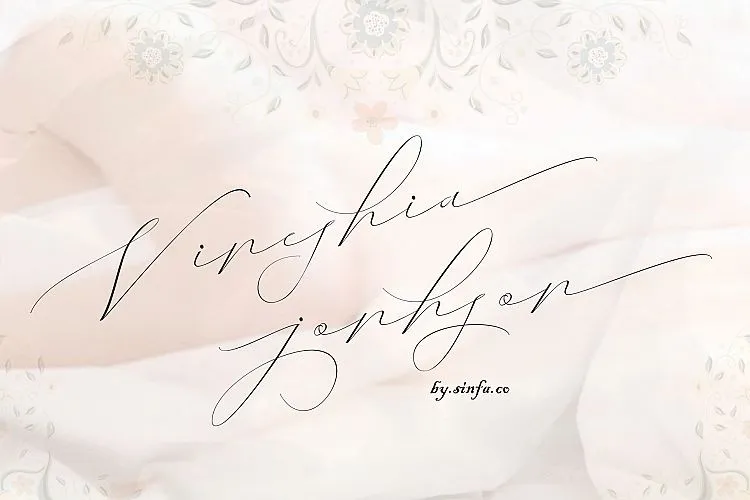
Vineshia Jonhson Handwritten Font – Fonte Grátis
Vineshia Jonhson Handwritten Font
Aqui está uma descrição em português para a página de download da fonte ‘Vineshia Jonhson Handwritten Font’, adaptada aos requisitos: Um novo conceito na categoria de fontes escrita à mão, essa moderna e feminina Vineshia Jonhson é perfeita para aqueles que desejam dar um toque único e criativo a seus projetos. Construída com uma estrutura elegante mas com traços casuais e bases variadas, permite criar um visual autêntico de escrita à mão. Esta fonte é ideal tanto para trabalhos manuais quanto para design tipográfico, permitindo que você realize diversas criações em poucas horas. Com seu desenho atrevido e sua personalidade única, a Vineshia Jonhson é uma excelente escolha para quem deseja estilizar suas composições de forma moderna e diferenciada. Ela não apenas simplifica o processo de criação de tipos em diversos projetos, mas também ajuda a tornar o trabalho com as letras mais divertido e gratificante. A Vineshia Jonhson é uma fonte à mão que traz um toque singular ao design gráfico, proporcionando resultados imediatamente visíveis. Suas linhas delicadas e texturas variáveis não apenas permitem criar um estilo único para seus trabalhos de arte, mas também tornam o processo mais agradável e menos estressante. Esta fonte é uma excelente opção tanto para projetos profissionais quanto para criações artísticas pessoais, oferecendo um toque moderno e elegante ao seu trabalho.